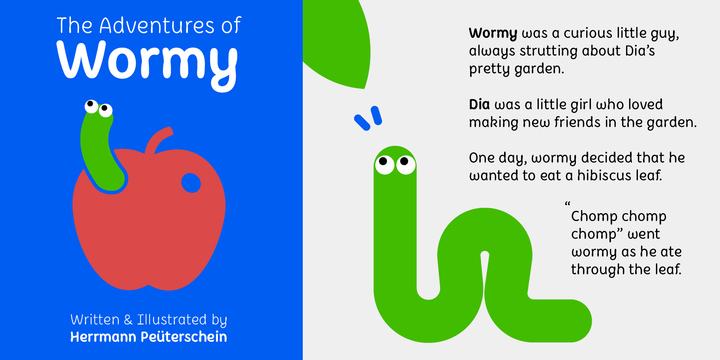
Mit der ComicJens bin ich immer noch nicht ganz zufrieden, aber es war schwer, eine
verspielte, etwas tollpatschige Schrift zu finden, die aber auch noch auf unruhigem
Hintergrund funktioniert...Solltet Ihr dazu noch Ideen haben, dann gerne her damit.